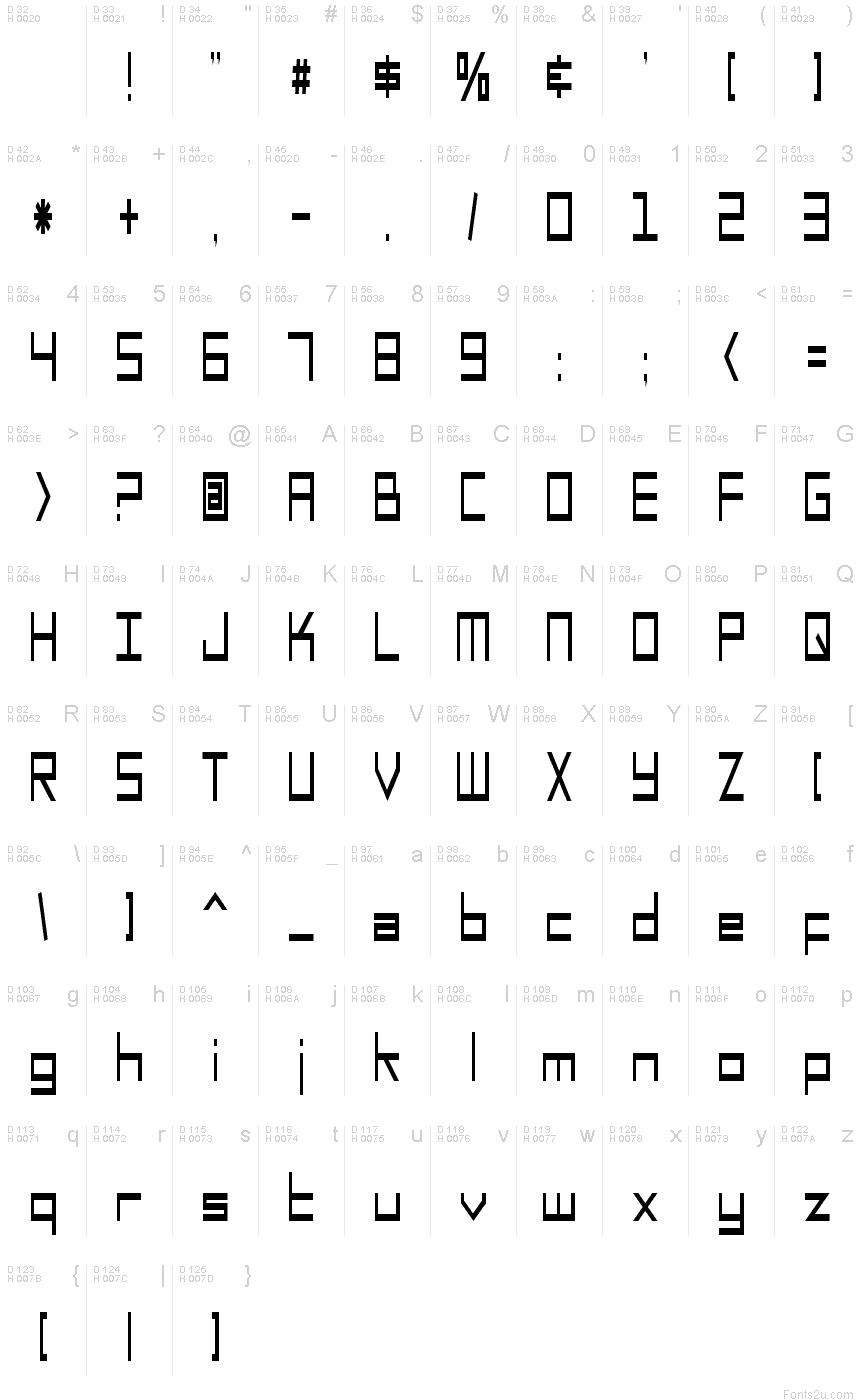
SF Square Head Condensed, darmowy font displayowy w stylu techno od ShyWedge z 1999 roku, przywołuje surowy klimat ery automatów arcade dzięki klockowym, prostokątnym literom i głębokim wcięciom w narożnikach. Projekt sprawia wrażenie zbudowanego ze kwadratowych ścieżek, a nie kreślonego ręcznie, co nadaje alfabetowi sztywny, oparty na siatce rytm, który czyta się jako wyraźnie cyfrowy i nieco industrialny.
Naturalnie pasuje do logo gier, ulotek muzyki elektronicznej, nagłówków plakatów, czołówek i opakowań sci-fi, gdzie ta zamknięta w pudełku geometria nadaje krótkim słowom realnej prezencji. Jako darmowy font sprawdza się również w zinach, brandingu inspirowanym interfejsami i kompaktowych tekstach na okładkach, które potrzebują twardego, syntetycznego brzmienia bez popadania w generyczny futuryzm.